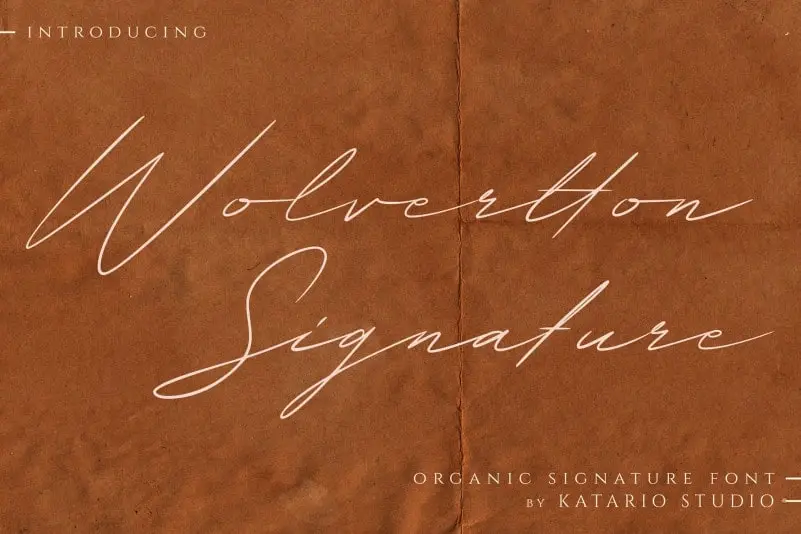
Wolvertton Signature Font – Fonte Grátis
Wolvertton Signature Font
A Wolvertton Signature Font é uma elegante mão-de-vizinha perfeita para projetos minimalistas que valorizam a simplicidade e sofisticação. Seu design, criado pelo designer Hamilton, incorpora um toque orgânico e natural, proporcionando um estilo elegante e elegante que brilha em designs de logotipos de alta qualidade, projetos de marca, convites para casamentos e muito mais. A Wolvertton é uma fonte escrita à mão, com uma presença irresistível devido a seu estilo autêntico e despreocupado, onde suas linhas fluídas e caracteres fluidos se encaixam perfeitamente em qualquer projeto gráfico. Engane-se se pensar que é um design convencional: esta fonte é um toque de vida para qualquer layout ou interface digital. Seja você designer web, ilustrador ou criativo gráfico, a Wolvertton Signature Font é uma escolha inteligente para seus projetos, oferecendo uma harmonia perfeita entre simplicidade e estilo.